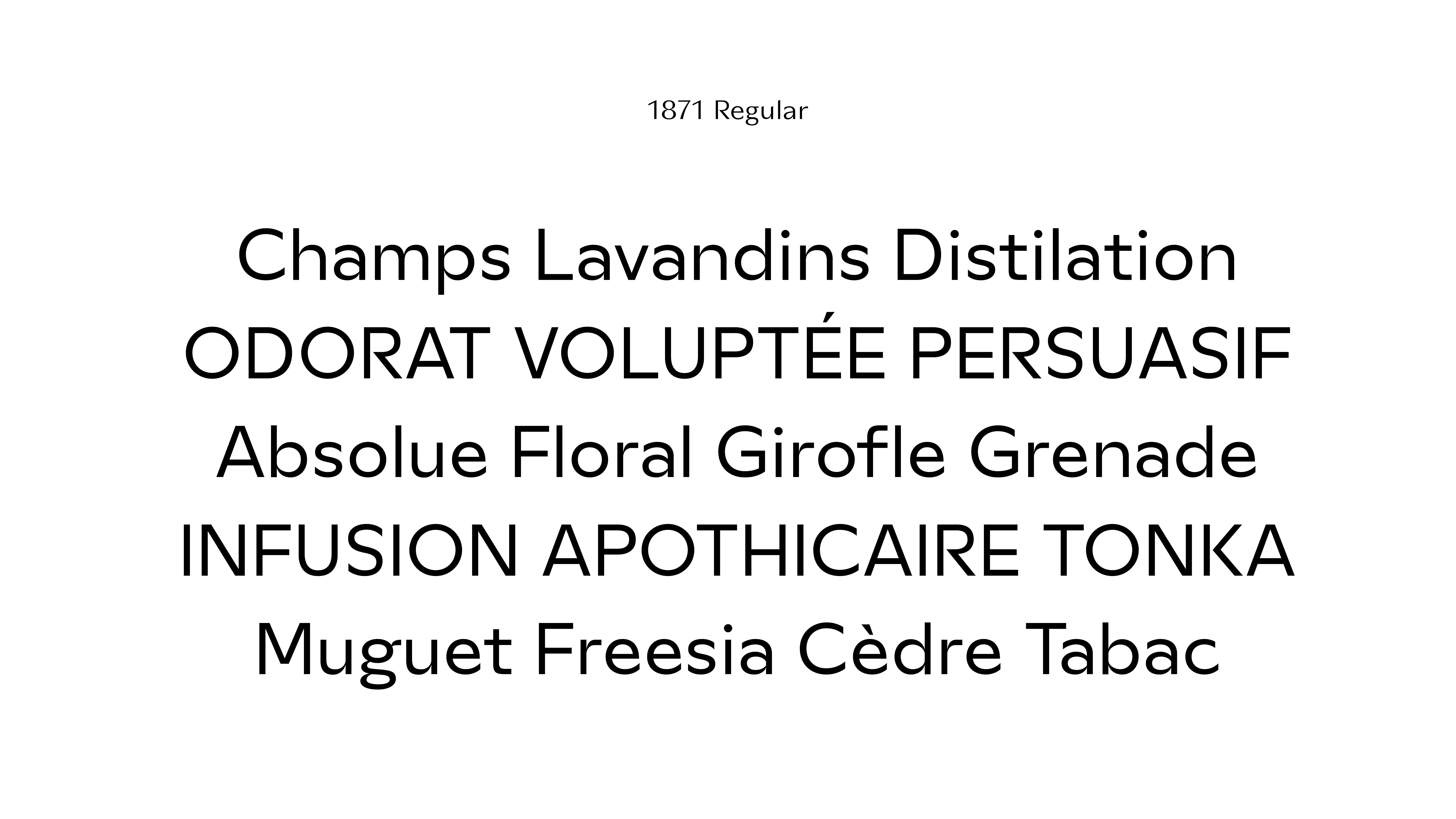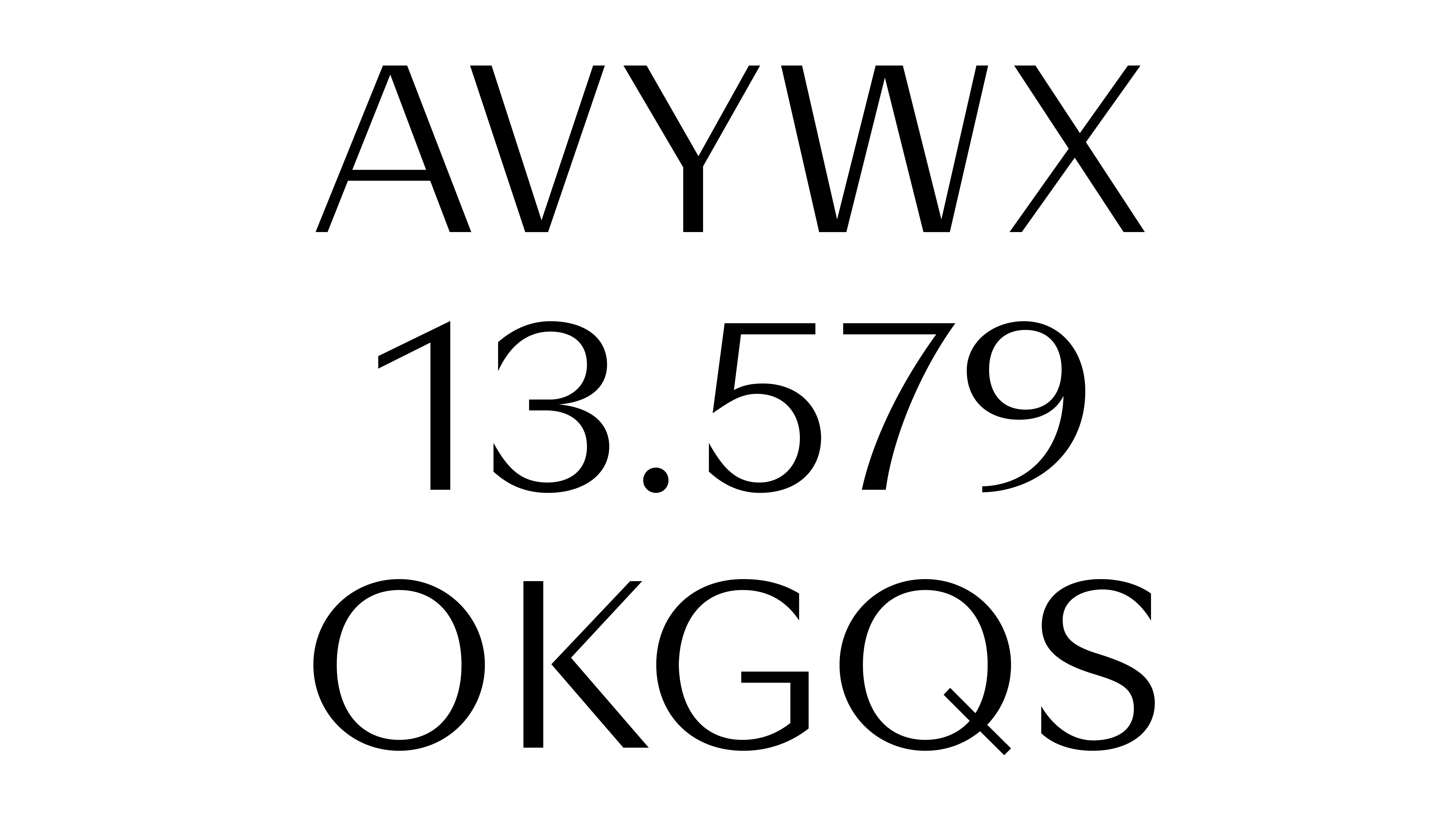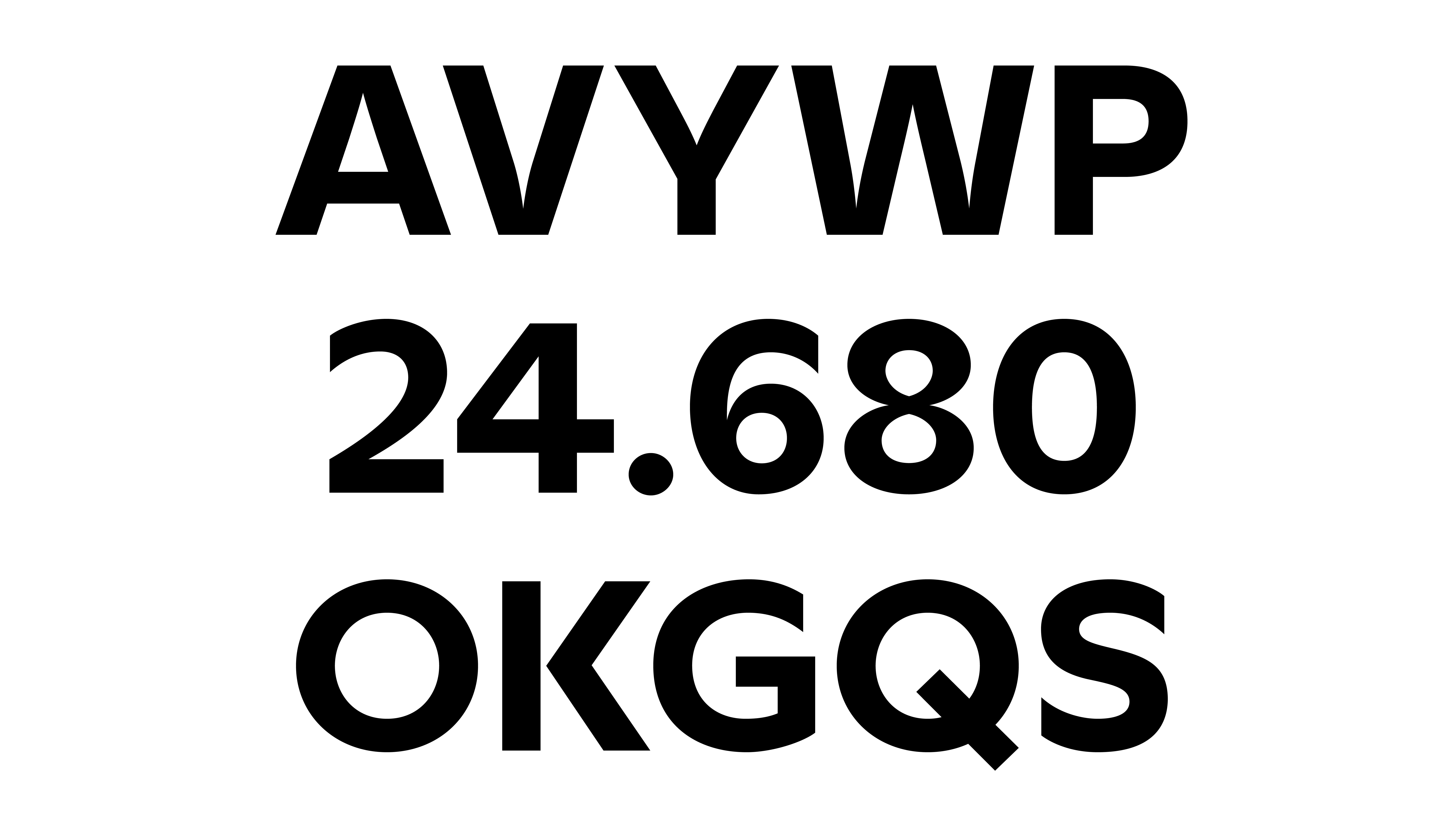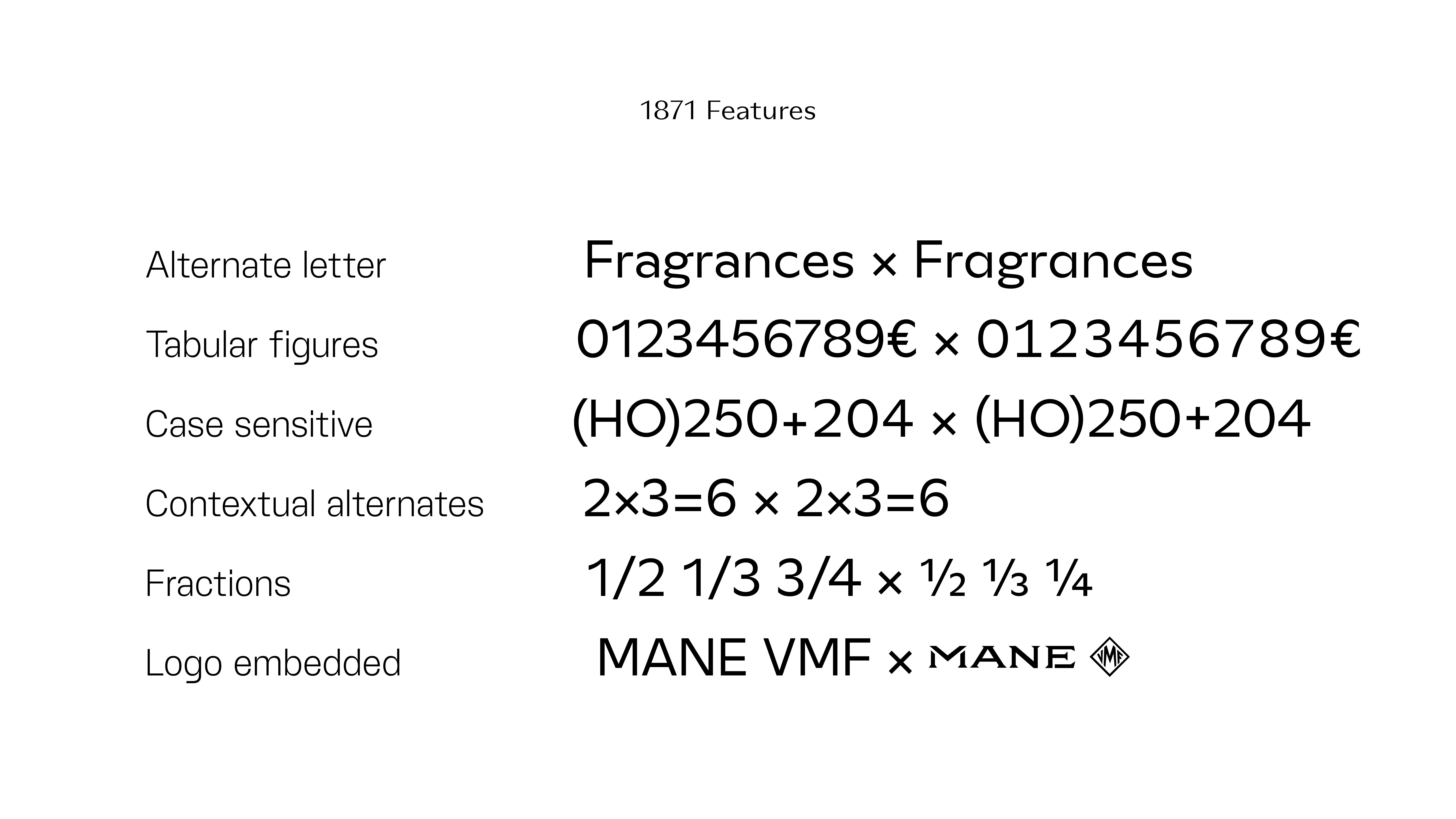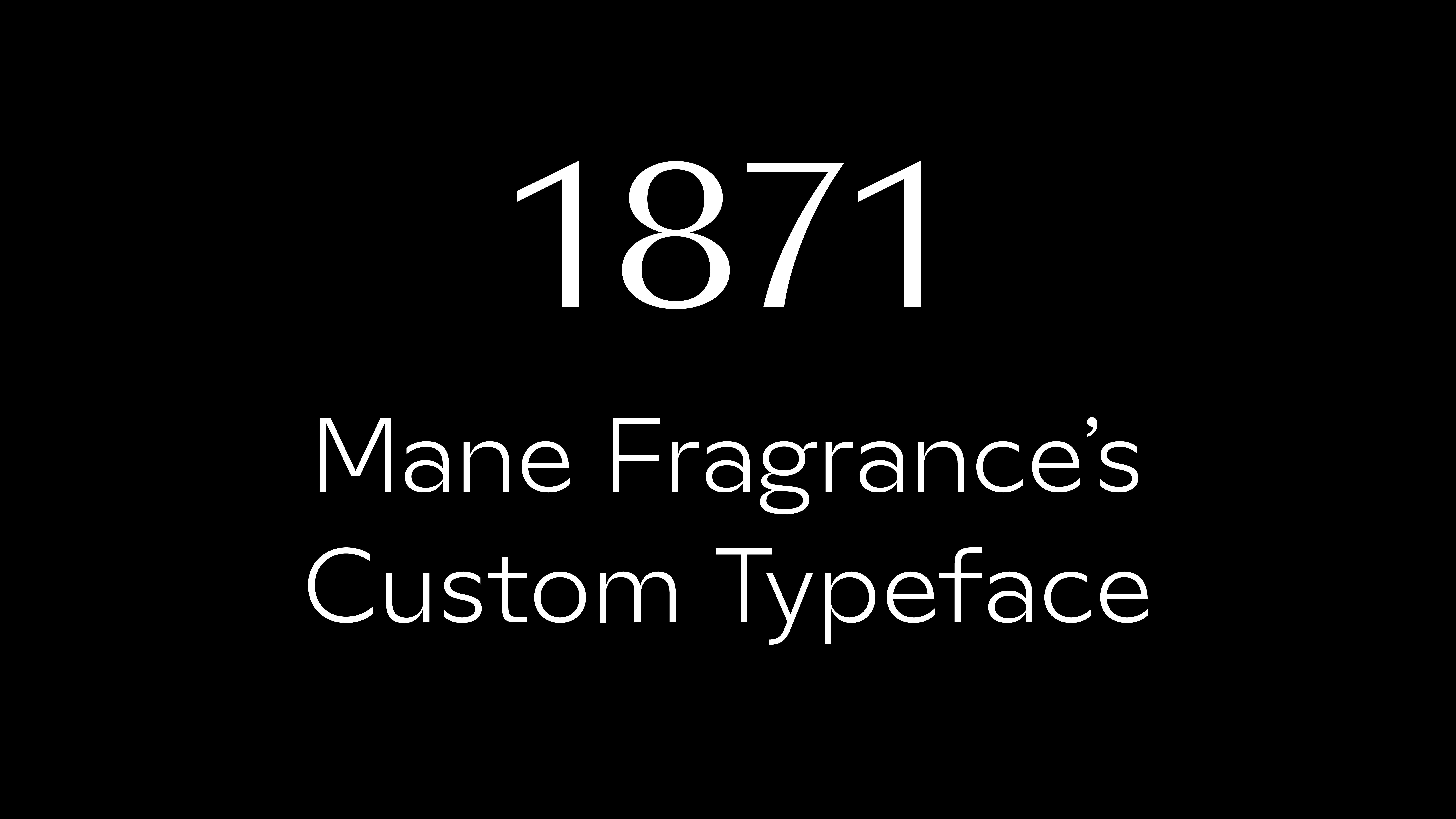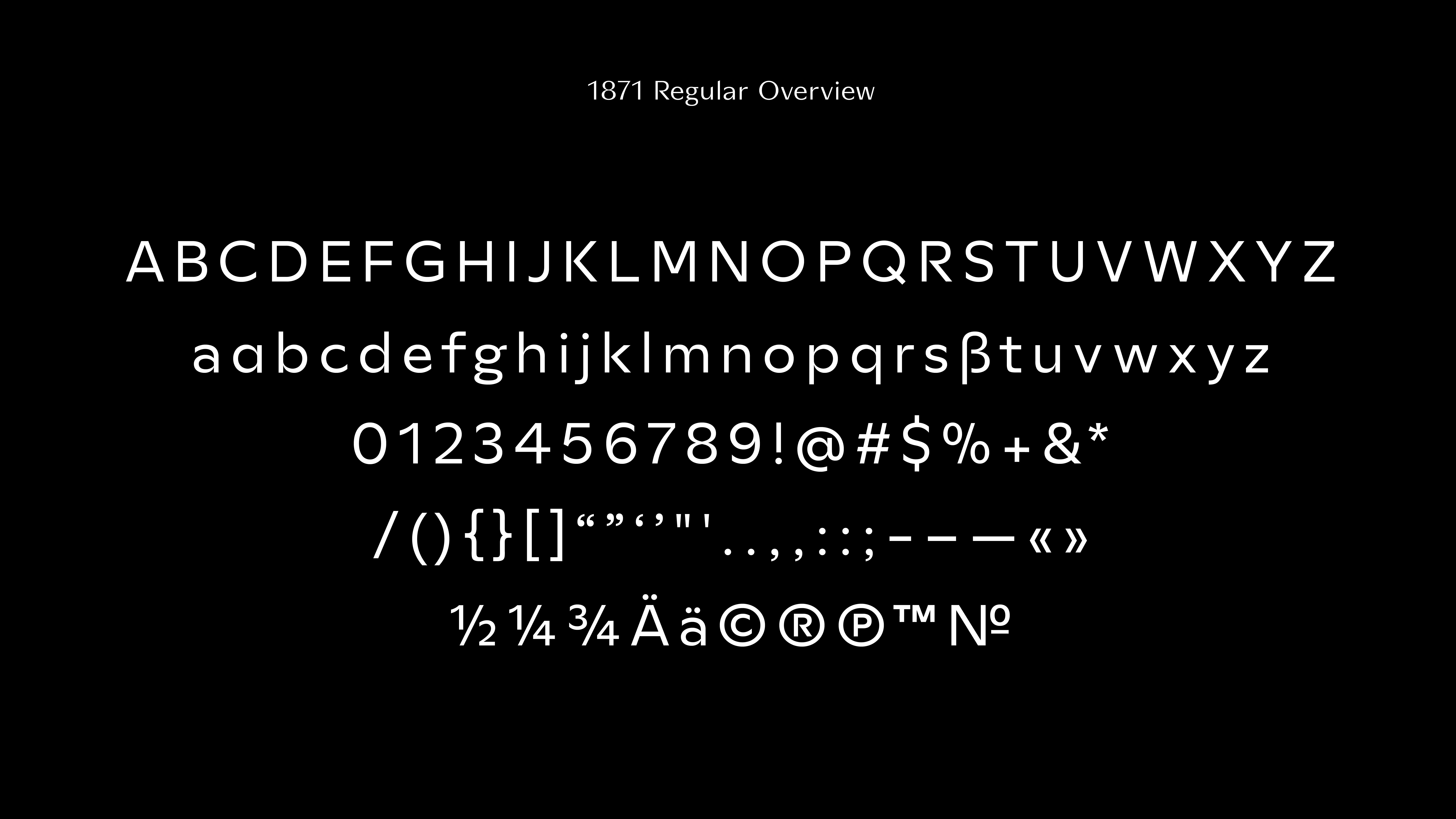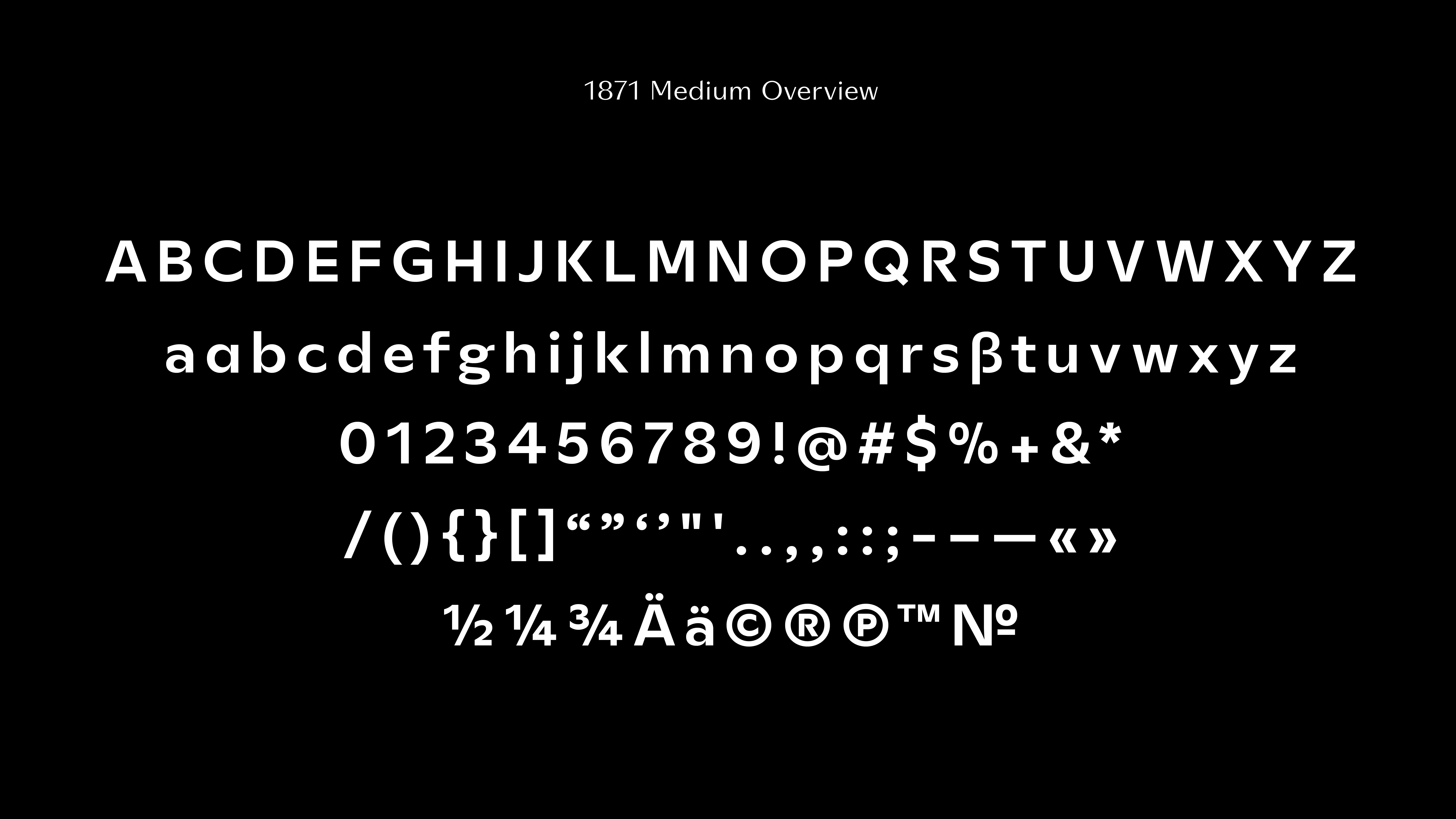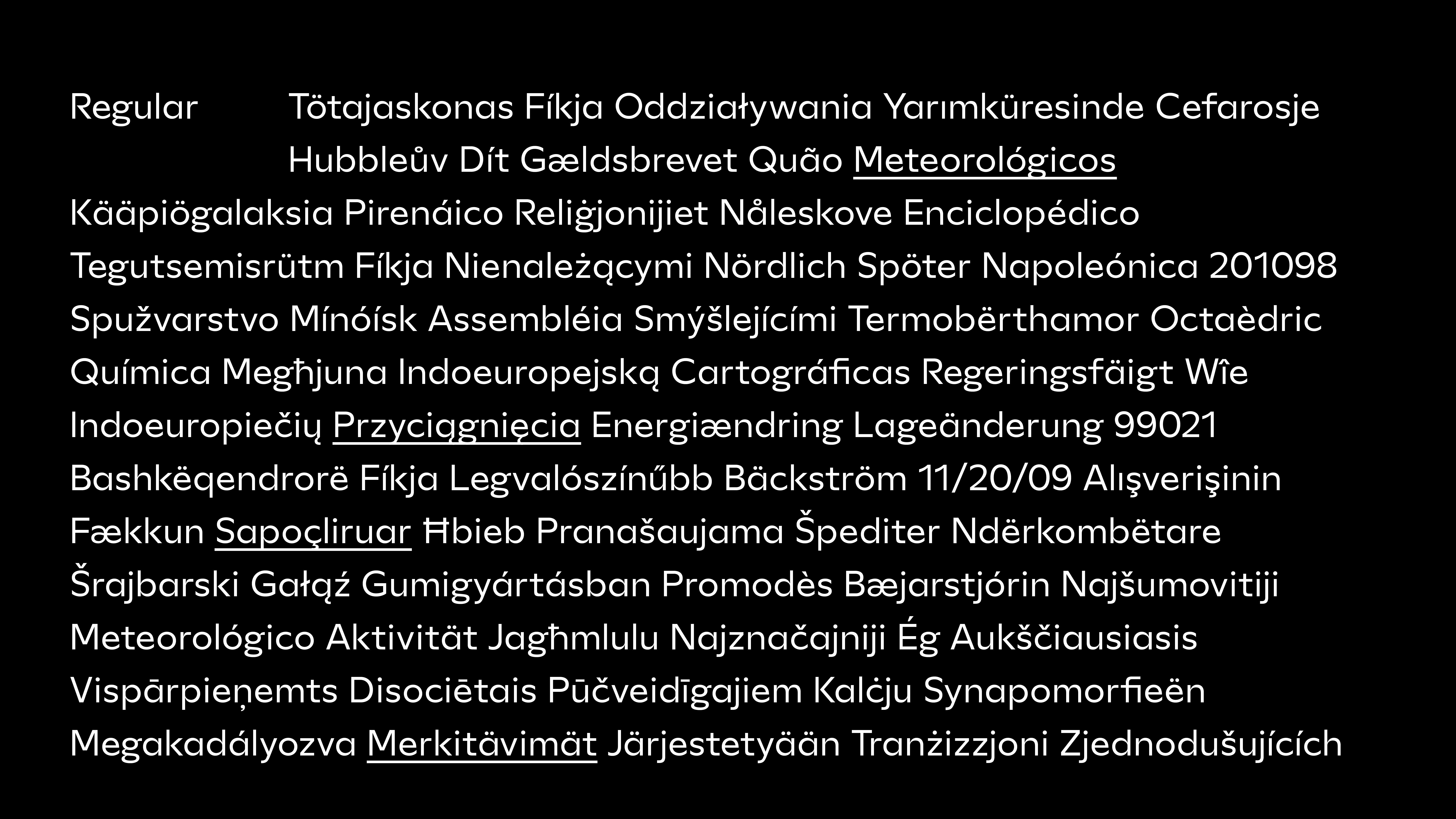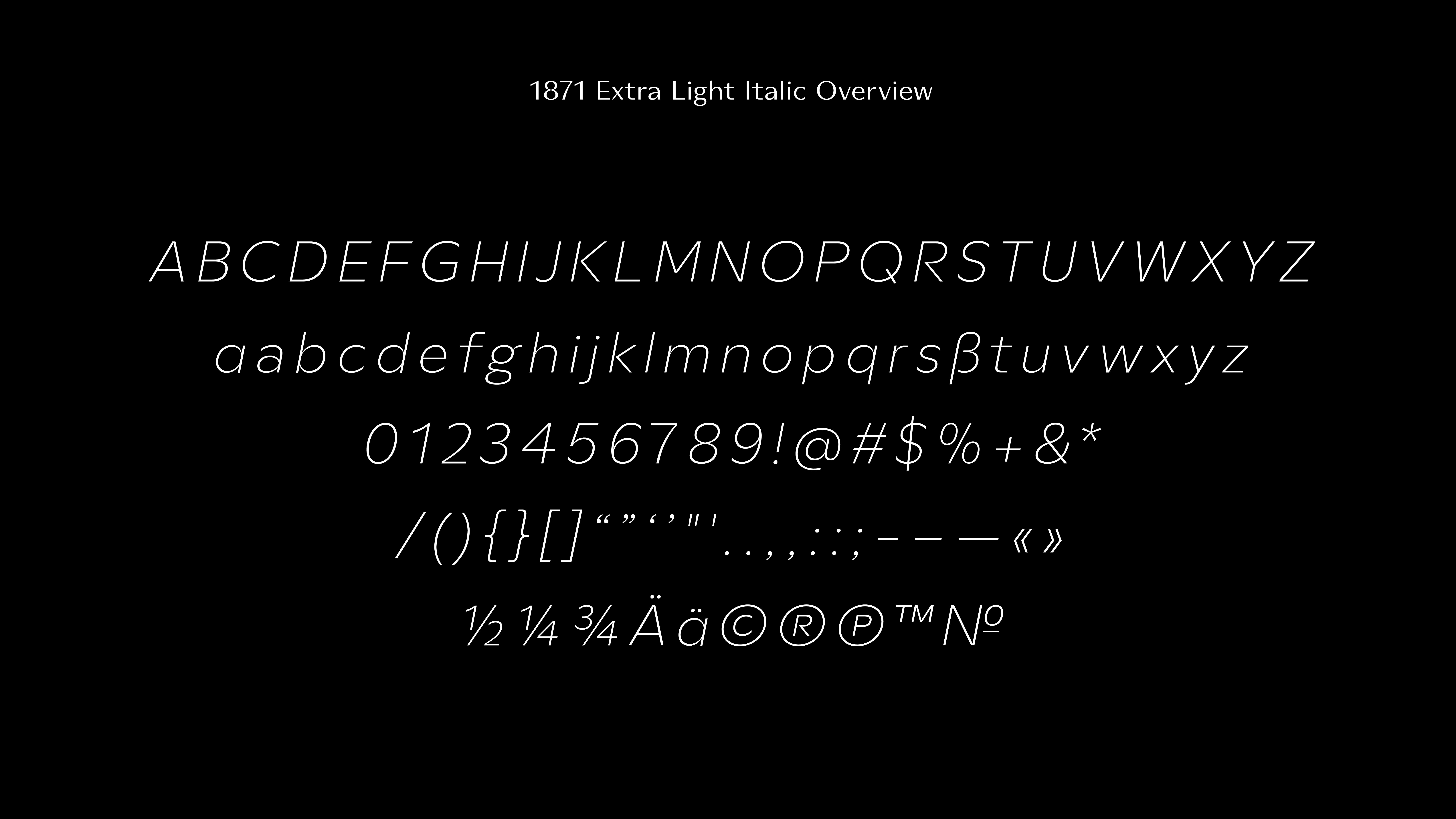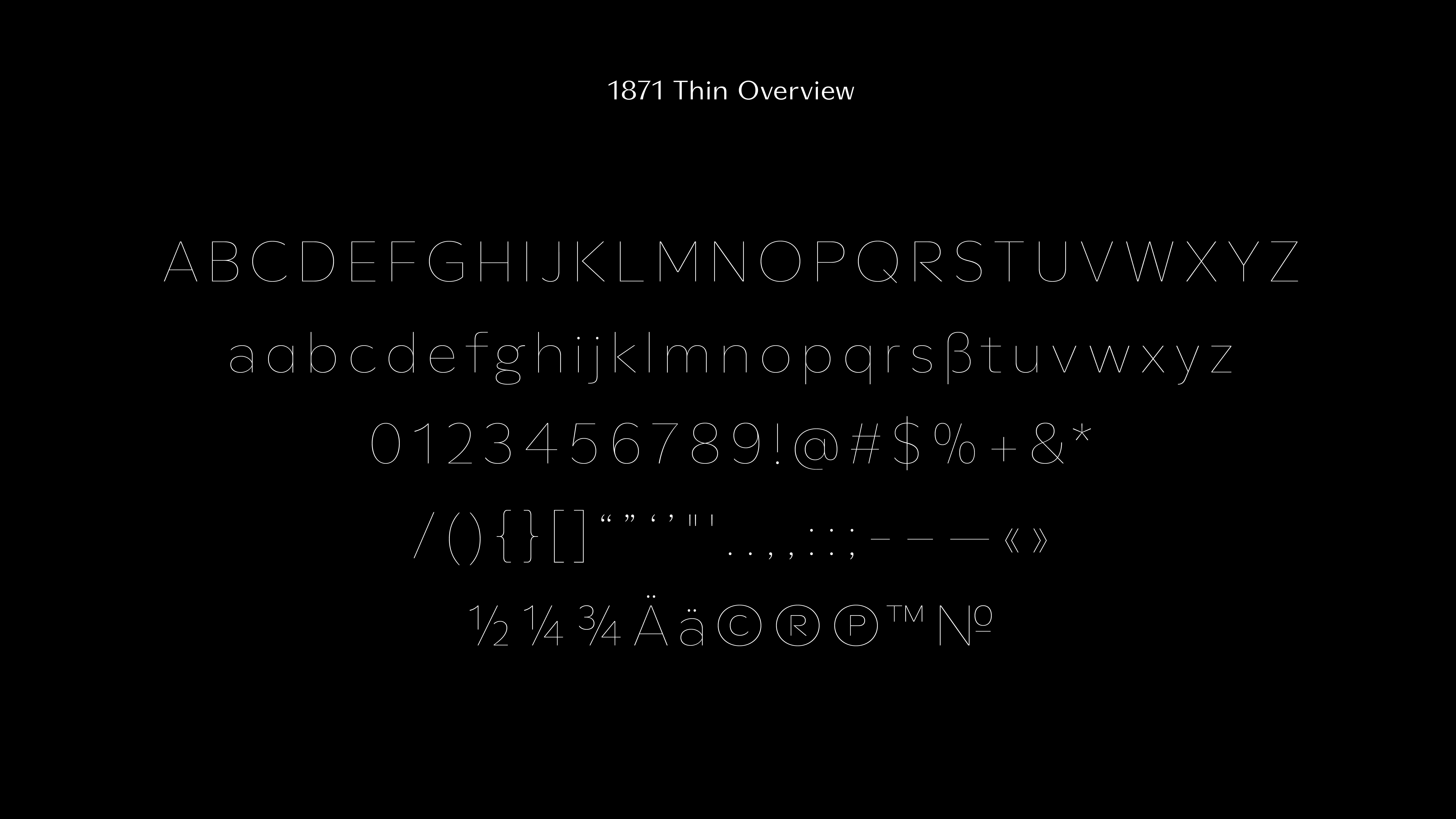
1871 Custom Font-Family
1871 est la nouvelle typographie identitaire de Mane Fragrance,
l'un des acteurs historiques dans la création de parfums et d'arômes en France.
La société a été établie en 1871 par Victor Mane dans la région de Grasse.
Sa conception a été construite selon une synthèse de recherches autour des polices de caractères italiennes des années 30 ainsi que de l’univers typographique se référant au mouvement ‘Art Déco’. Le challenge résidait dans la conception d’un caractère typographique identitaire pouvant se mêler à l’identité visuelle existante tout en ayant une forte personnalité emprunte de l’ADN de Mane.
Dans la volonté d'ancrer cette future famille typographique dans le territoire historique de la marque, de nombreuses spécificités ont été apportées. De manière générale et en référence au logo original toujours en vigueur, la chasse de la 1871 est large et le caractère possède un gros œil autant en Display qu’en Texte. Le contraste entre pleins et déliés de la version Display prends ses racines dans les Didots françaises de la fin 19ème, alors que les médianes décentrées sont une référence au style ‘Art Déco’.
Plus en détails, les connexions des bas-de-casse entre les courbes et les fûts sont affinées et acérées. Enfin les terminaisons, incisives en Display, verticales en version Texte, sont longues et ouvertes cela procurant un bel élan dans le dessin et rendant la lecture facilitée par son horizontalité.
1871 est une famille complète comprenant deux versions. Toutes deux de classification ‘sans-serif’. Une version Display, contrastée et une version Texte avec sept graisses et deux italiques.
Mane Fragrance Custom Font-Family